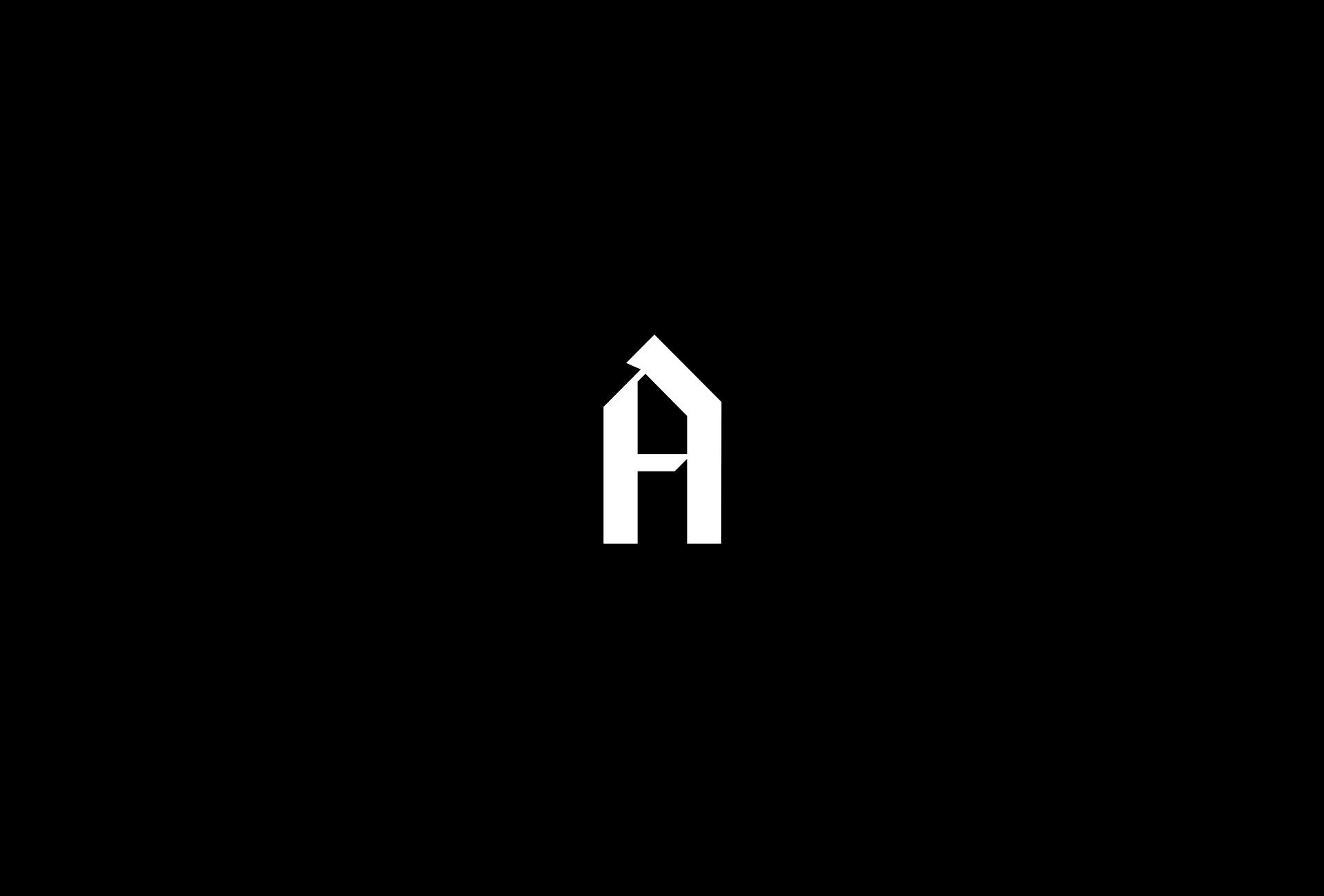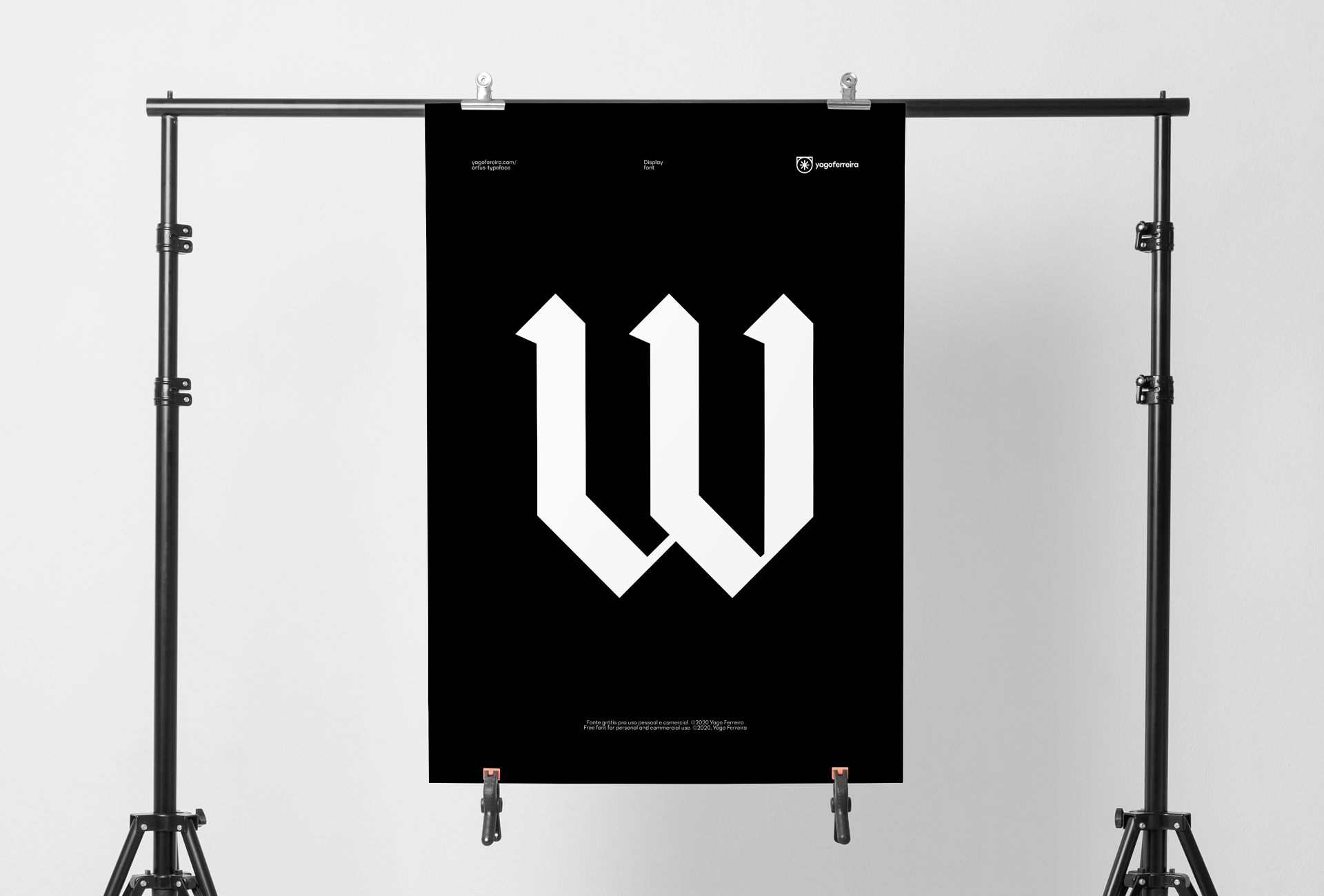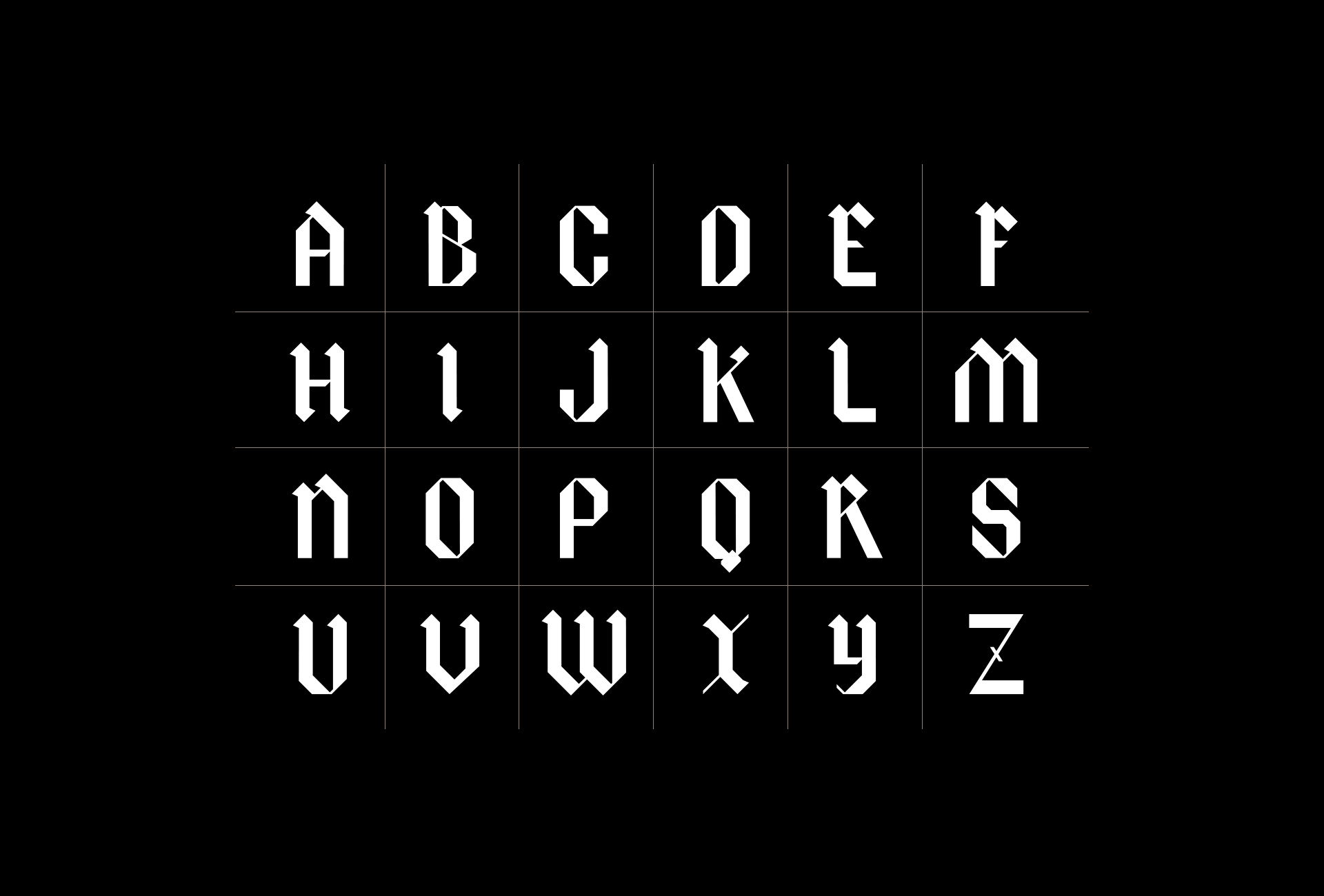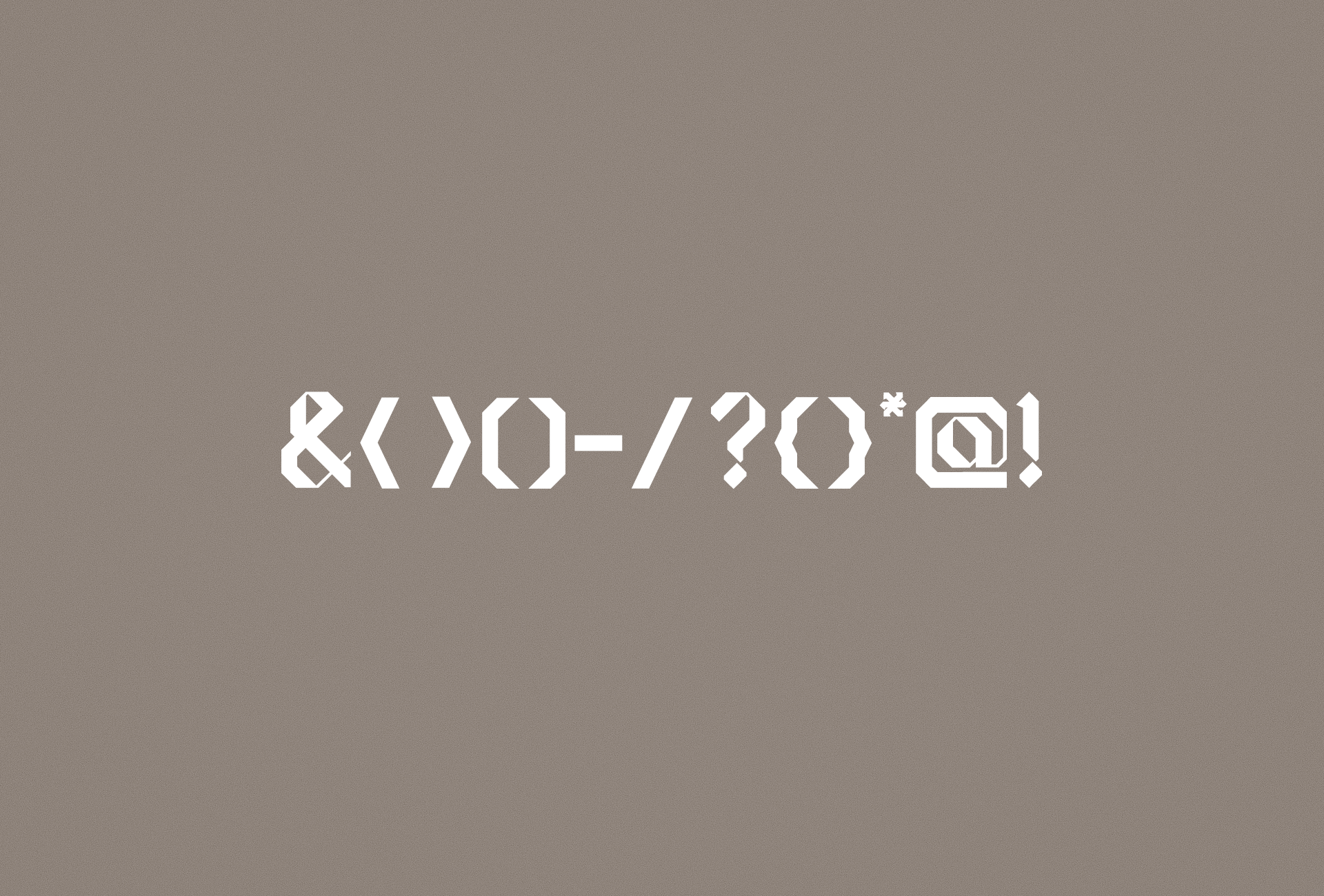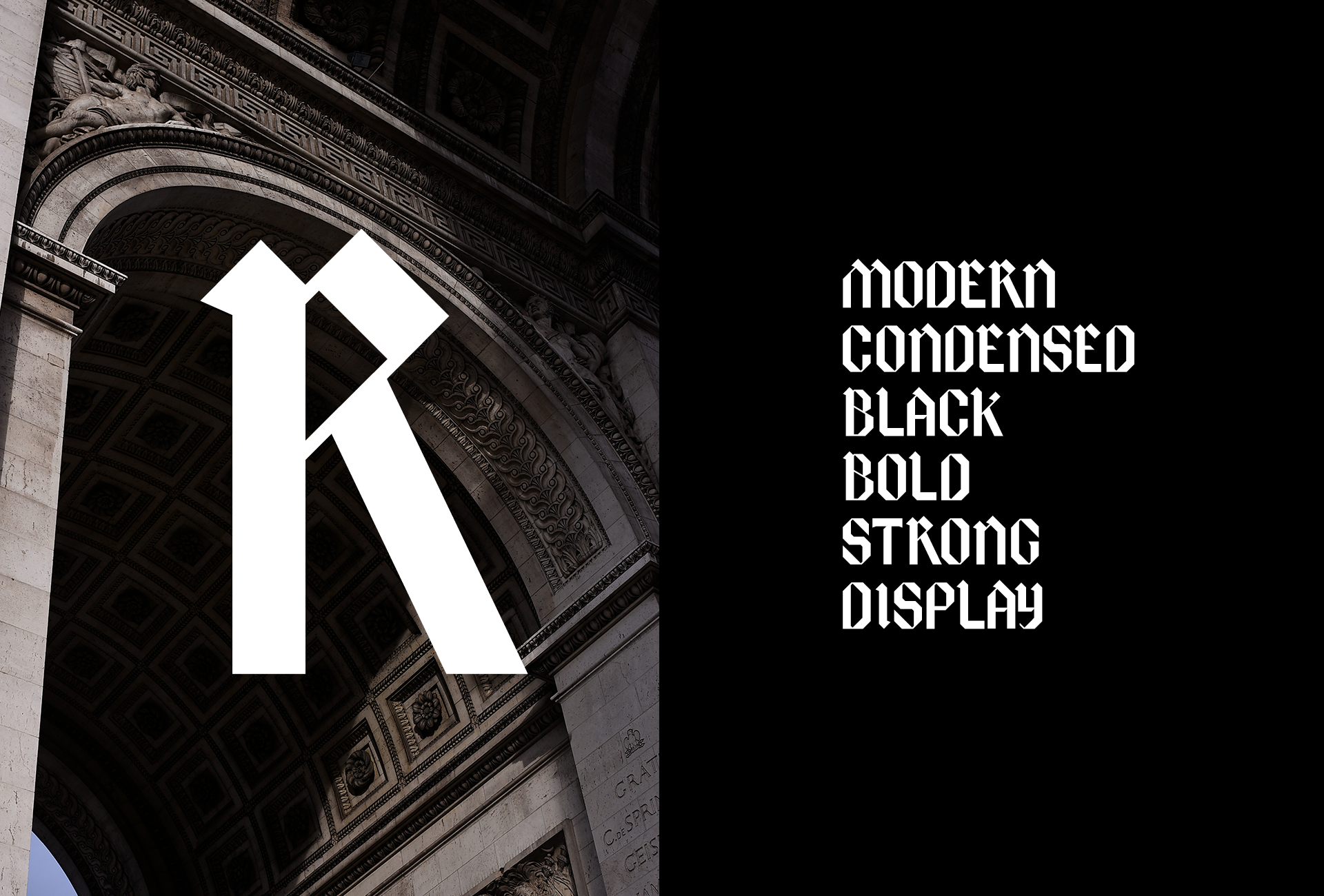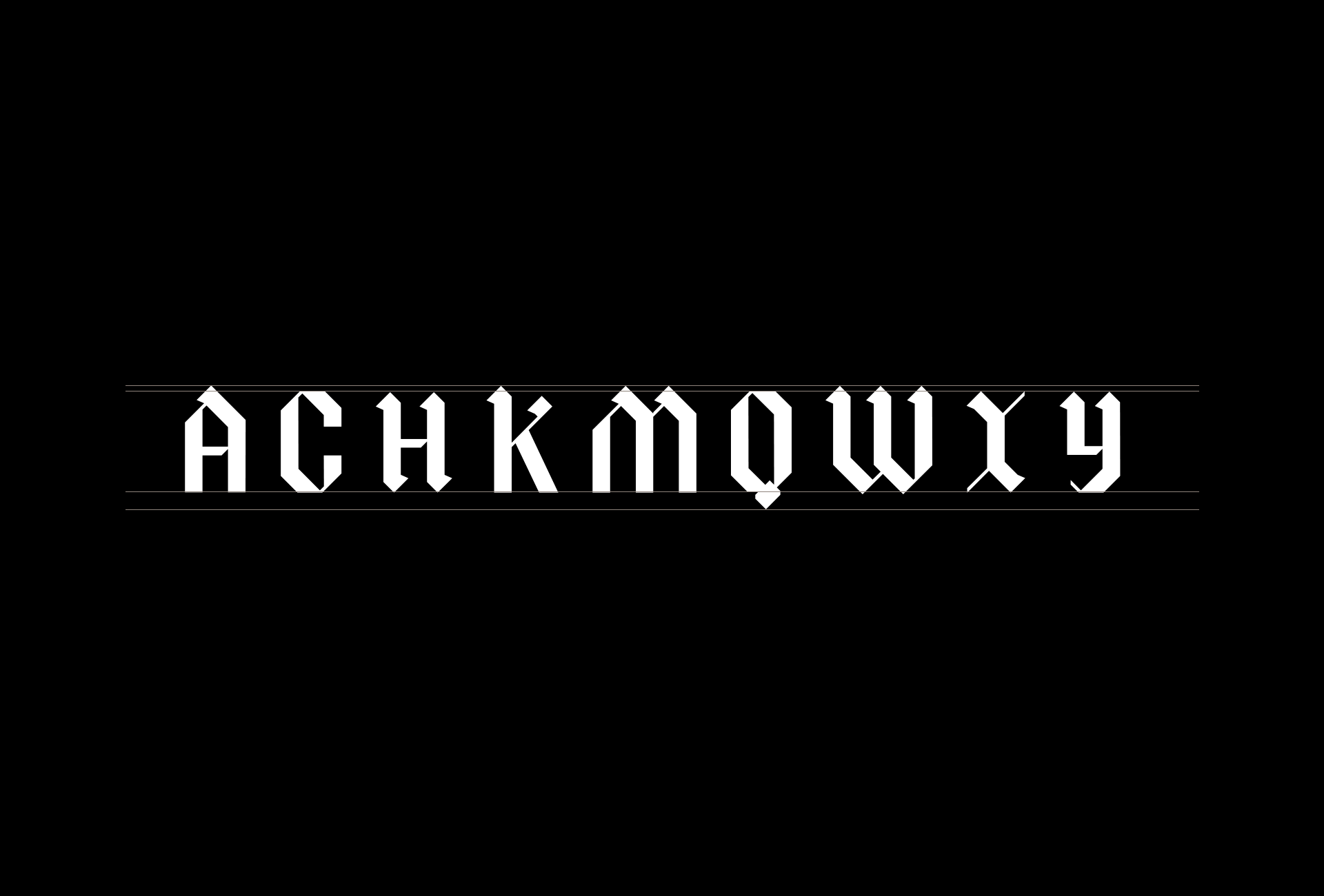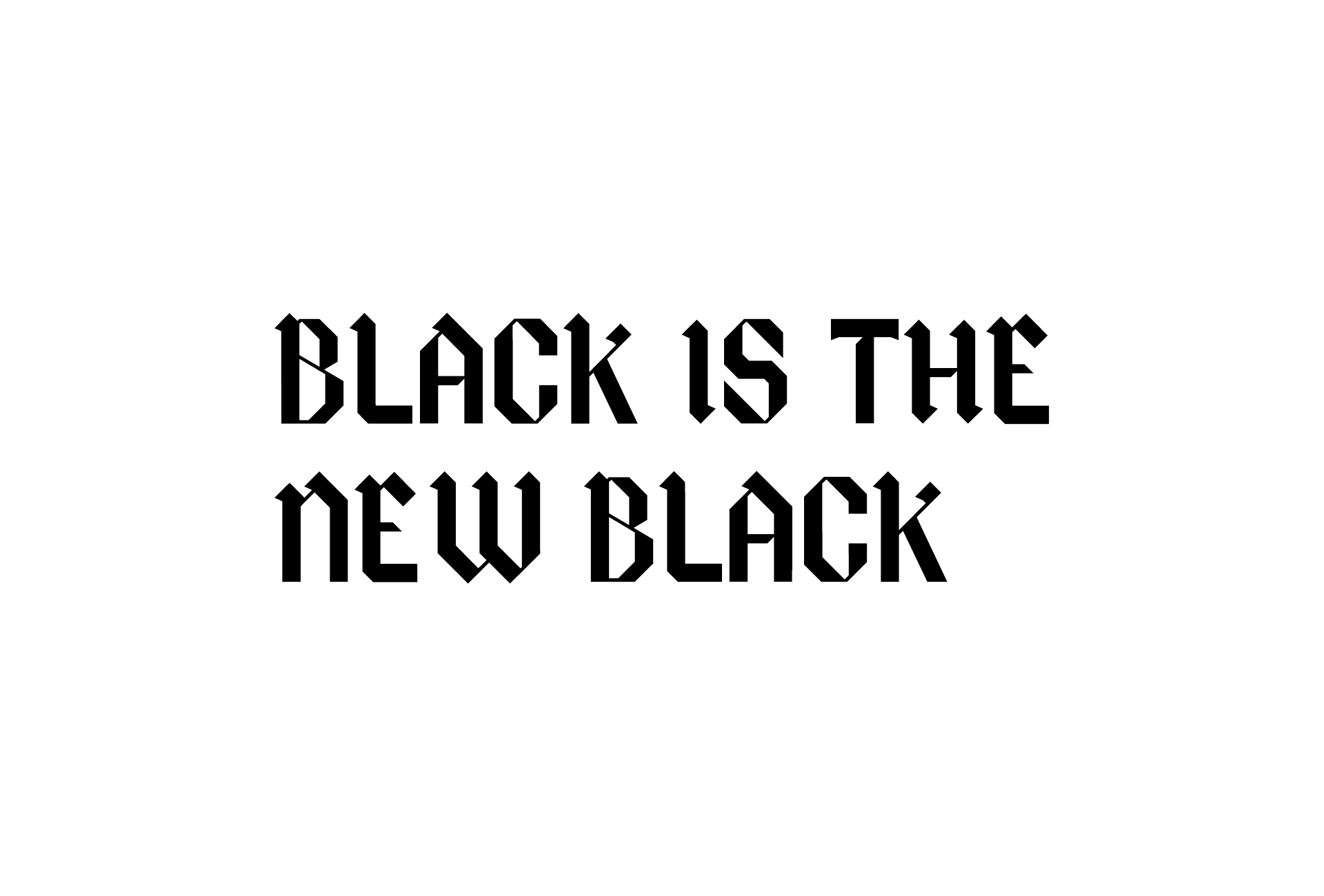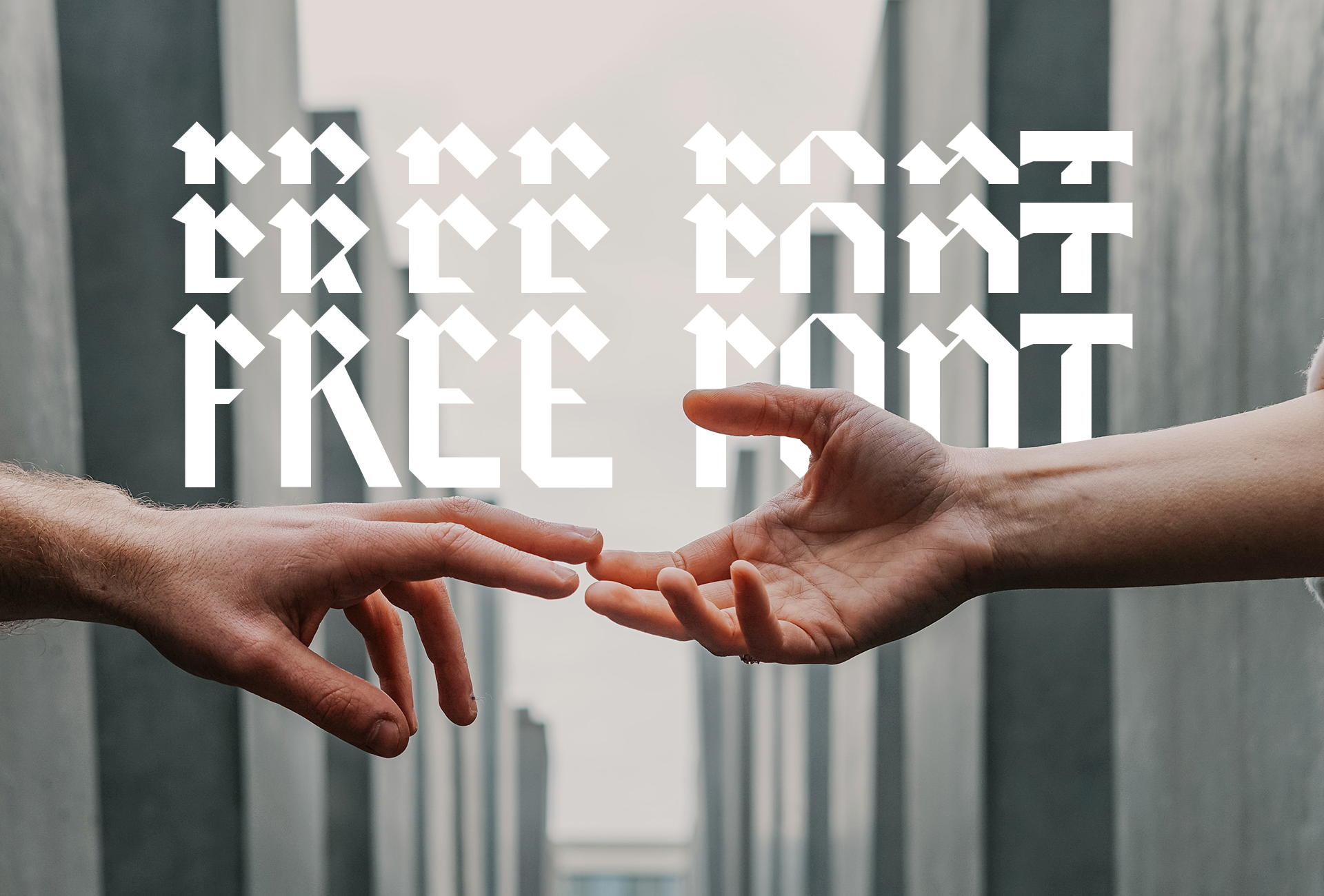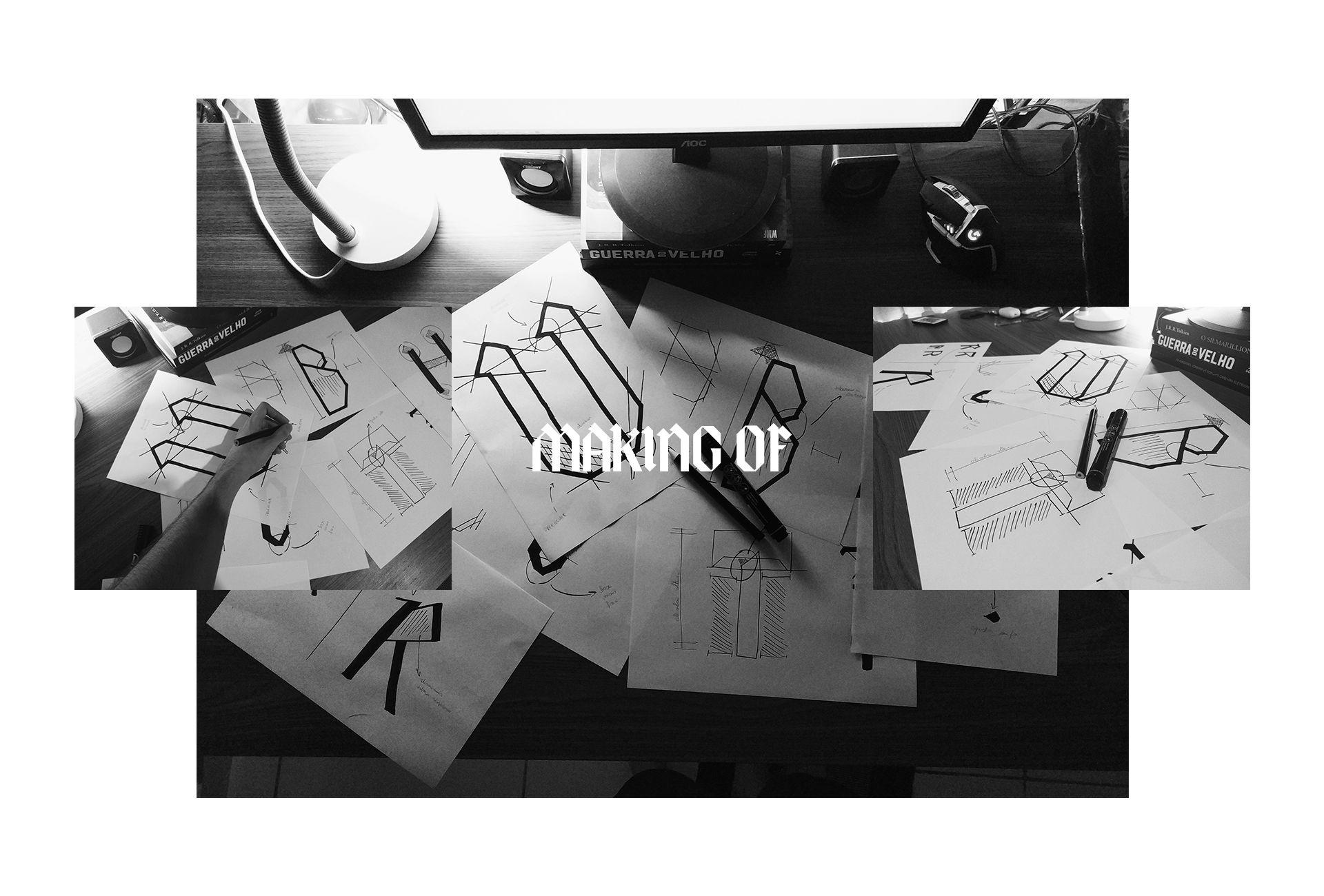
ORTUS TYPEFACE / 2020
Ortus é uma exibição de fonte em letras pretas condensada desenvolvida para títulos
expressivos. Suas linhas retas tornam a fonte mais condensada tornando a escrita
mais imponente. Feita a partir de um projeto pessoal durante a quarentena.
Ortus is a condensed black letter font display developed for expressive titles.
Its straight lines make the font more condensed making the writing more imposing.
Made from a personal project during quarantine.